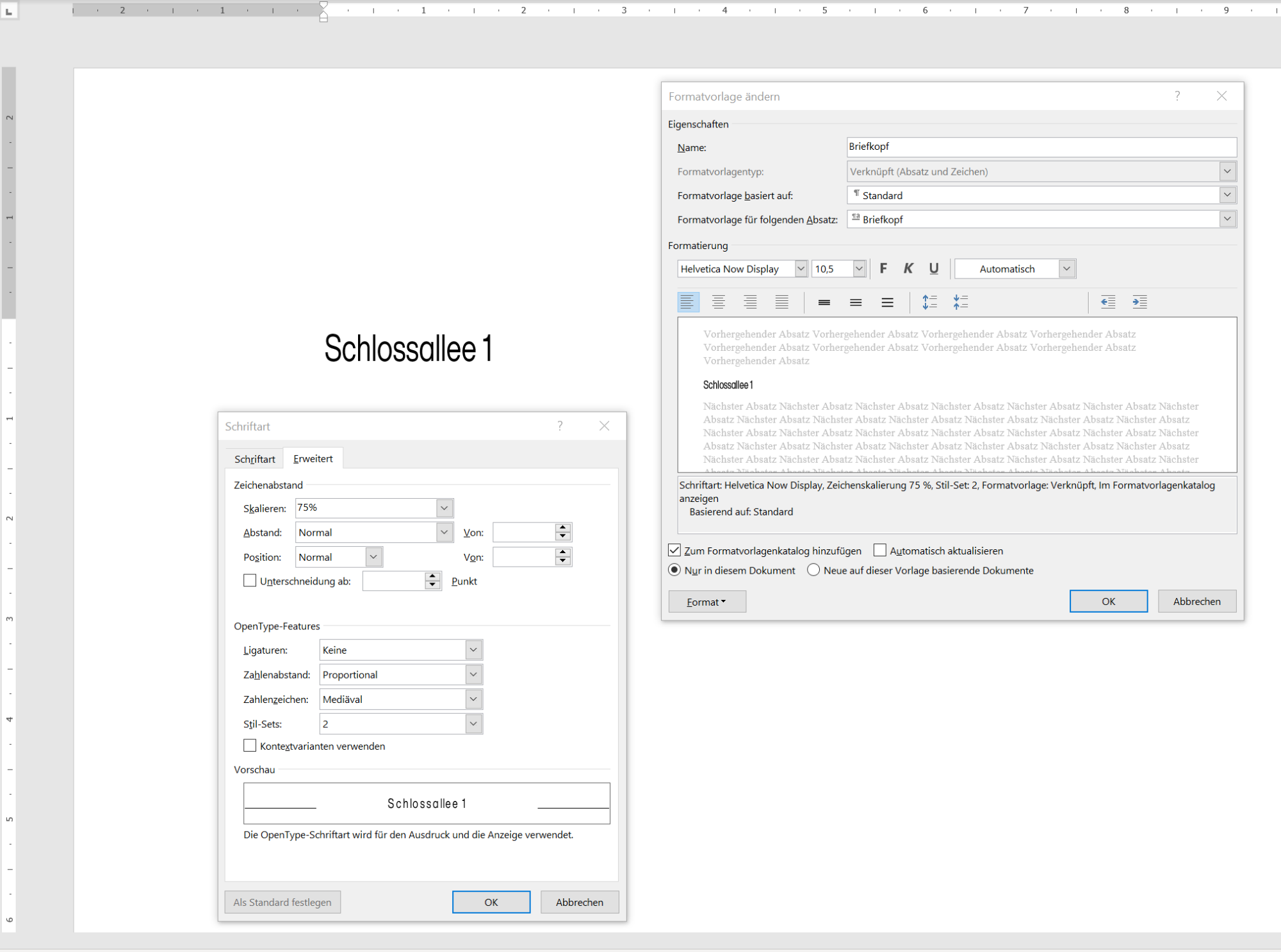
Briefkopf - Schrift für Brieftext
In naher Zukunft ziehe ich  um und daher möchte ich mich um einen neuen Briefkopf für mich kümmern. Auch wenn ich als Privatmann immer weniger Briefe schreibe, kommt immer mal der Moment. Und mein jetziger Briefkopf dürfte 20 Jahre auf dem Buckel haben. In dem verwende ich ausschließlich die Myriad Pro.
Für den neuen Briefkopf ist die Wahl auf zwei Schriften gefallen. Für meinen Namen die Askan Light Italic (18 Pt), die ich dafür ganz schön finde. Des weiteren habe ich mir vor einiger Zeit die Helvetica Now gekauft, die ich für die Anschrift und die weiteren Kontaktdaten einsetze (Helvetica Now Text Light in 11 Pt.)
Allerdings habe ich mit der Helvetica Now so viel herumgespielt (siehe Screenshot), dass ich jetzt ein Problem habe. Den Briefkopf erstelle ich mit Affinity Publisher, den will ich dann in Word als Hintergrund setzen. Nun wäre es nahe liegend, die Helvetica Now für den Brieftext zu nehmen, aber Word kann die ganzen Spezialitäten leider nicht. :cry:
Welche Schrift würdet Ihr mir für den Brieftext ans Herz legen?
Eigentlich tue ich mich auch schwer damit, mehr als zwei Schriften einzusetzen. Ein Ersatz der Aksan wäre denkbar, wenn es in ähnliche Richtung geht.
Auch wenn ich als Privatmann immer weniger Briefe schreibe, kommt immer mal der Moment.
aber Word kann die ganzen Spezialitäten leider nicht.
Da würde ich an Deiner Stelle eher drüber nachdenken, bei Affinity zu bleiben und dort auch den Textsatz zu machen, als zu Word zu wechseln um dann Kompromisse in der Schriftwahl machen zu  müssen – jetzt wo Du sie einmal lizenziert hast.
Sehe ich das richtig, dass die Helvetica um 25 % gestaucht werden soll?! 🥺
Da würde ich an Deiner Stelle eher drüber nachdenken, bei Affinity zu bleiben und dort auch den Textsatz zu machen, als zu Word zu wechseln um dann Kompromisse in der Schriftwahl machen zu  müssen.
Da bin ich eher pragmatisch. Nach dem Umzug muss man vielen die neue Adresse mitteilen. Es gibt eine Excel-Tabelle für einen Serienbrief. Und das kann der Affinity-Publisher nicht. Andererseits wird es den meisten Empfängern herzlich egal sein, welche Schrift verwendet wird - solange es keine Fraktur ist. :lol: Ich denke mal darüber nach.
Sehe ich das richtig, dass Du Fonts um 75 % stauchst?! 🥺
Ähm - "auf" wäre wohl richtig - nicht "um". Ist das eine Sünde? Die neue Straße ist einfach deutlich länger als mein Name. Dafür suchte ich eine Lösung. Aber ich bin Anfänger. Also sind Tipps auch dazu willkommen!
Edit: Sieht so aus...
Ähm - "auf" wäre wohl richtig - nicht "um".
Hatte ich bereits korrigiert.
Ist das eine Sünde?
In meinen Augen eine Art typografische, ja! Weil die Horizontalen jetzt fetter werden als die Vertikalen. Es war aber andersherum gedacht. So wird der Font ästhetisch entstellt.
Serienbrief
Ah, daran hatte ich nicht gedacht.
Also sind Tipps auch dazu willkommen!
1. Ein schmallaufende Schrift verwenden 👉🏻 #condensed #narrow
2. Wenn es vertretbar ist, die Schriftgröße minimieren
Ist das eine Sünde?
Nein. Aber Murks. Suche dir doch einfach für die komplette Adresse (also inklusive des Namens) eine schöne schmale Schrift, so wie von R::bert empfohlen. Dann hast du, egal wie du dich für den Brieftext entscheidest, insgesamt nur zwei Schriften in der Gestaltung. Eventuell kannst du es ja so machen, dass du für den Briefkopf eine Antiqua/Serif verwendest und für den Text eine Grotesk/Sans – oder umgekehrt.
Ein Ersatz der Aksan wäre denkbar, wenn es in ähnliche Richtung geht.
Das verstehe ich nicht. Verwendest Du für diese denn auch OT-Features? Warum nicht in Affinity ein Basislayout erstellen, als PDF für den Hintergrund in Word importieren und dann dort mit der Aksan weiterschreiben?
Hallo @Typo-Newbie, mal ganz abgesehen von der qualitativen Beurteilung deines Vorhabens (bitte nimm dir die Hinweise meiner Vorredner zu Herzen): rein auf der technischen Ebene sind Skalierung und Stil-Sets, also die von dir so genanten »Spezialitäten«, in MS Word ohne Weiteres verfügbar. Wenn du mehrere Stil-Sets aktivieren möchtest, musst du zwar Formate verschachteln (1 Stil-Set pro Format). Da das aber für deinen Briefkopf ein einmaliger Aufwand ist, sollte das vertretbar sein.
Als Mensch, der häufig mit Menschen mit eingeschränkten Fähigkeiten zu tun hat, würde ich dringend vom Stauchen absehen, sondern stattdessen die entsprechenden Schriftschnitte, die hoffentlich vom Schriftkünstler auch unter Berücksichtigung der Lesbarkeit gestaltet wurden, wählen. Auch Light-Schriften haben so ihre Barrieren und sind sehr empfindlich, was Papier und Druck anbelangt.
Hallo zusammen!
Danke für Eure zahlreichen und hilfreichen Tipps. :-D
Am 26.10.2020 um 18:34 schrieb R::bert:
In meinen Augen eine Art typografische, ja! Weil die Horizontalen jetzt fetter werden als die Vertikalen. Es war aber andersherum gedacht. So wird der Font ästhetisch entstellt.
Am 26.10.2020 um 18:41 schrieb R::bert:
1. Ein schmallaufende Schrift verwenden 👉🏻 #condensed #narrow
2. Wenn es vertretbar ist, die Schriftgröße minimieren
Am 26.10.2020 um 18:54 schrieb Norbert P:
Nein. Aber Murks. Suche dir doch einfach für die komplette Adresse (also inklusive des Namens) eine schöne schmale Schrift, so wie von R::bert empfohlen. Dann hast du, egal wie du dich für den Brieftext entscheidest, insgesamt nur zwei Schriften in der Gestaltung. Eventuell kannst du es ja so machen, dass du für den Briefkopf eine Antiqua/Serif verwendest und für den Text eine Grotesk/Sans – oder umgekehrt.
Okay, ich habe für mich mitgenommen, dass es keine gute Idee ist, eine Schrift zu stauchen. Ich lerne noch und nehme gern Wissen und Vorschläge auf.
Die Schrift für die Adresse zu verkleinern ist leider keine Option. Ich bin schon bei 11 Punkten angekommen und kleiner möchte ich nicht - übrigens auch nicht im Fließtext. Also werde ich mich wohl nach einer schmaleren Schrift umschauen und mir die Listen, die Ihr mir verlinkt habt, anschauen.
Gestern ist mir beim Stöbern übrigens aufgefallen, dass die Futura Now im  Angebot ist und es da auch eine schmale Variante gibt.
https://www.myfonts.com/fonts/mti/futura-now/text-condensed-regular/?meta=/399472/Schlossallee/Futura+Now+Text+Condensed+Regular/
Aber ich schaue mir erstmal die Liste an.
Würdet Ihr eigentlich eher für den Text eine Antiqua oder Grotesk nehmen? Mir scheint, dass es da kein einheitliches Bild gibt. :twisted:
Am 26.10.2020 um 18:54 schrieb R::bert:
Das verstehe ich nicht. Verwendest Du für diese denn auch OT-Features? Warum nicht in Affinity ein Basislayout erstellen, als PDF für den Hintergrund in Word importieren und dann dort mit der Aksan weiterschreiben?
Die Askan war seinerzeit ein Impulskauf. Mir gefällt, wie mein Name damit ausschaut und meine derzeitige Adresse. Aber im Fließtext fallen mir immer mehr Sachen auf, die mir nicht gefallen. Auf mich wirkt der Text sehr unruhig. Ich würde sie nicht als Fehlkauf abtun, aber eben nur für kurze Texte verwenden wollen.
https://www.myfonts.com/fonts/hoftype/askan/regular/?meta=/371300/Schlossallee+2040/Askan+Regular/
Am 26.10.2020 um 19:25 schrieb D2C:
Hallo @Typo-Newbie, mal ganz abgesehen von der qualitativen Beurteilung deines Vorhabens (bitte nimm dir die Hinweise meiner Vorredner zu Herzen): rein auf der technischen Ebene sind Skalierung und Stil-Sets, also die von dir so genanten »Spezialitäten«, in MS Word ohne Weiteres verfügbar. Wenn du mehrere Stil-Sets aktivieren möchtest, musst du zwar Formate verschachteln (1 Stil-Set pro Format). Da das aber für deinen Briefkopf ein einmaliger Aufwand ist, sollte das vertretbar sein.
Würdest Du mir bitte genauer erklären, wie Du das meinst und machst? Ich habe das mit dem Verschachteln probiert. Aber wenn ich Stil-Sets heben sich gegenseitig auf. Wähle ich "runde Punkte" aus und dann das "runde a" - sind die Punkte wieder eckig. :cry:Oder meinst Du je Buchstaben eine eigene Formatvorlage, bis es passt?
vor einer Stunde schrieb Typo-Newbie:
Also werde ich mich wohl nach einer schmaleren Schrift umschauen
Nur interessehalber, warum möchtest Du eine möglichst schmale Gestaltung? Hast Du ein Platzproblem? Oder geht es um die Anmutung von Luftigkeit? Oder verbindest Du eine Emotion damit?
Hast Du schon mal geschaut, wie Dein Briefkopf mit unteschiedlichen Kontrasten aussieht? Also Name wie bisher, darunter aber eine normale Schrift mit nur 75% Deckung?
Und über was für einen Drucker (bzw. dessen Fähigkeiten) verfügst Du? Light- und schmallaufende Schriften können abhängig von Drucker und Papier schnell zermanschen, insbesondere in kleineren Größen.
Am 26.10.2020 um 18:06 schrieb Typo-Newbie:
Die neue Straße ist einfach deutlich länger als mein Name. Dafür suchte ich eine Lösung.
Nachdem die Straße vermutlich weniger wichtig ist als der Name, könnte man sie auch kleiner setzen. Dann wird der Straße-Schriftzug auch kürzer.
Am 28.10.2020 um 09:34 schrieb Typo-Newbie:
Würdet Ihr eigentlich eher für den Text eine Antiqua oder Grotesk nehmen? Mir scheint, dass es da kein einheitliches Bild gibt. :twisted:
Es gibt auch noch eine dritte Möglichkeit speziell für Brieftexte, die es sich lohnt in Betracht zu ziehen. Antiqua oder Grotesk sind ja Kategorien für Satzsschriften, die erst einmal formal auch so wirken, also »wie gesetzt« und auch in der Anwendung so behandelt werden müssen, also nach den Regeln für Schriftsatz. Typografisch kann es da Sinn machen, auf Monospace-Schriften auszuweichen, also Schriften bei denen jeder Buchstabe die gleiche Breite mit Weißraum links und rechts einnimmt (d.h. Schreibmaschinen-Schriften, wie die Courier, die aus den technischen Beschränkungen des Geräts geboren wurden) – damit trennt sich auch die Ebene »offizieller« Angaben wie Namen, Adresse, Kontaktinformationen besser vom eigentlichen, immer veränderlichen Brieftext.
Ausserdem wären diese auch von Haus aus in der Strichstärke so robust ausgelegt, dass sie auch auf den unterschiedlichsten Ausgabegeräten nicht visuell wegbrechen, was vielleicht wichtig sein könnte, wenn das pdf einer Rechnung auch mal auf dem vielleicht nicht perfekt kalibrierten Bürodrucker des Auftraggebers ausgedruckt werden sollte … mit einem leichten Schnitt kann das eher schon mal passieren.